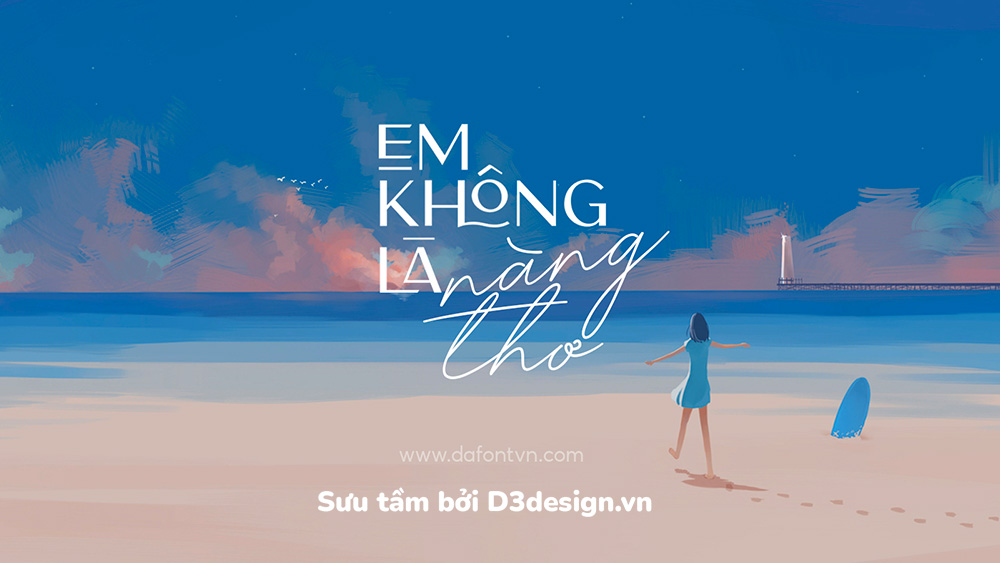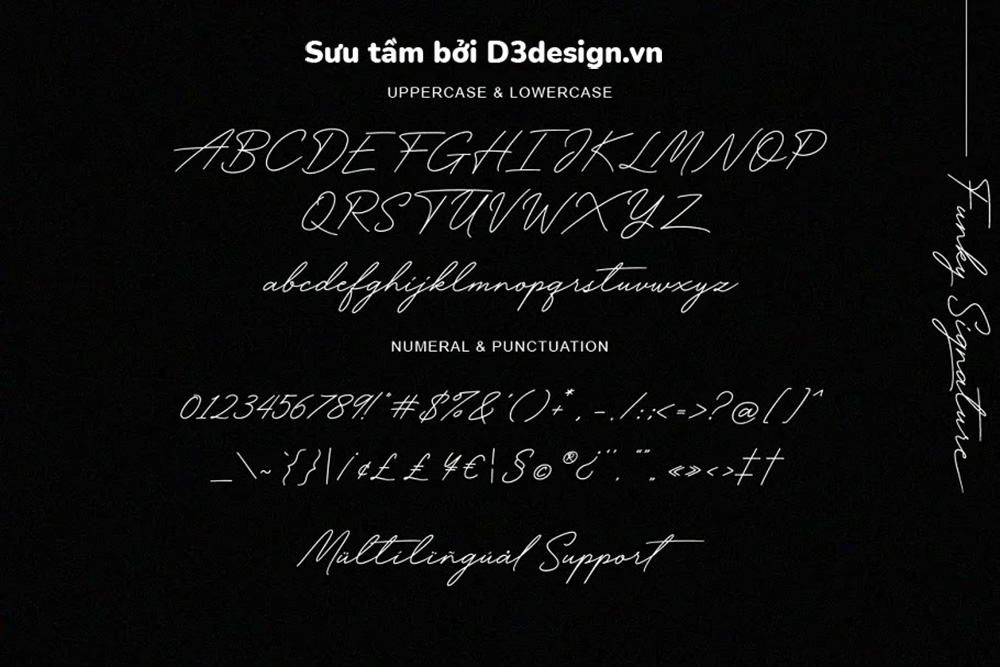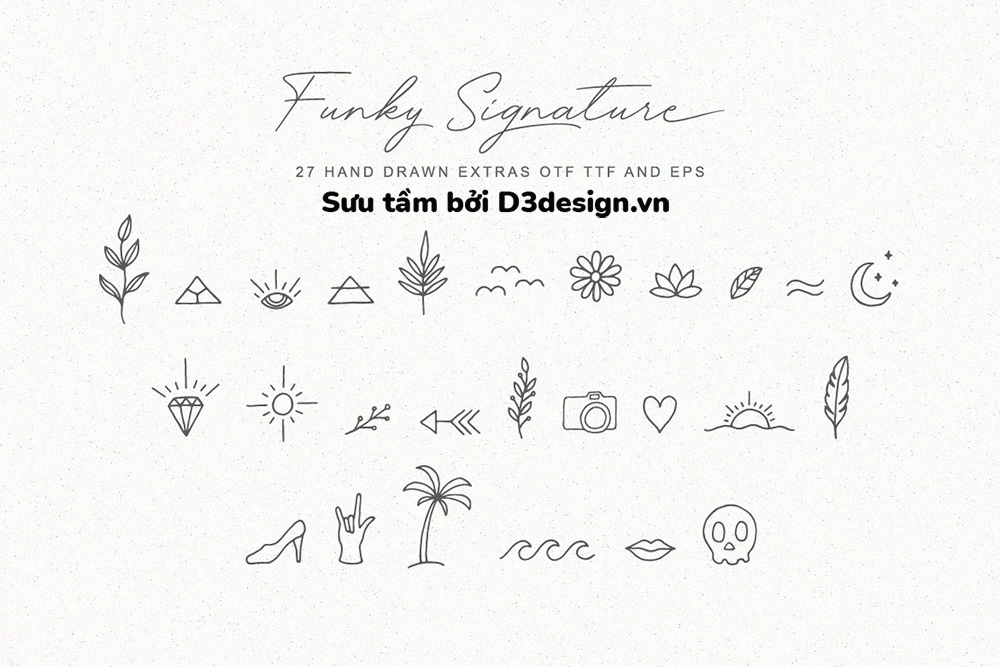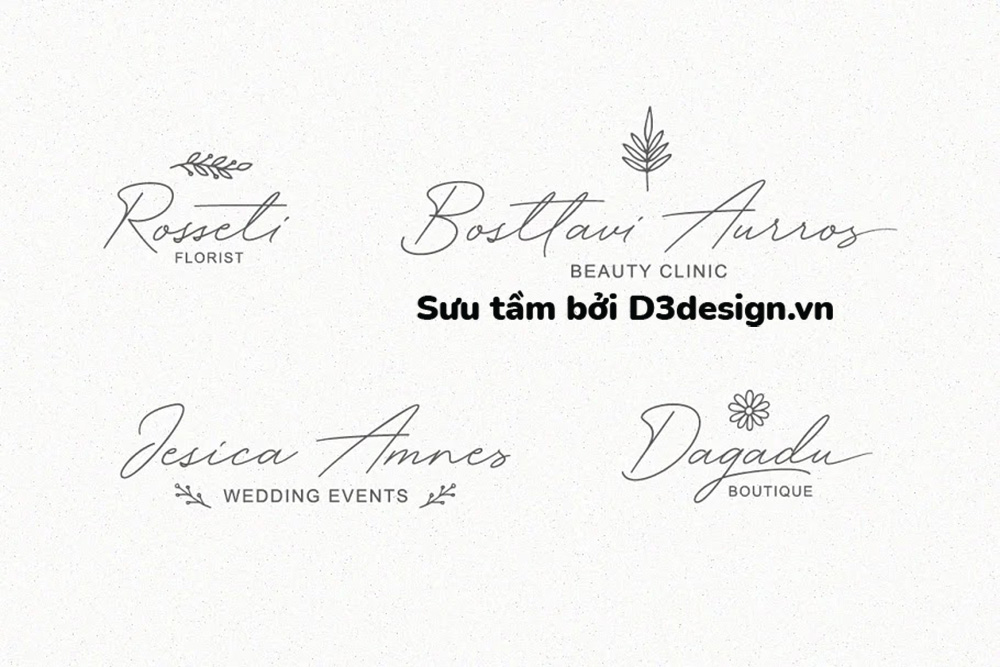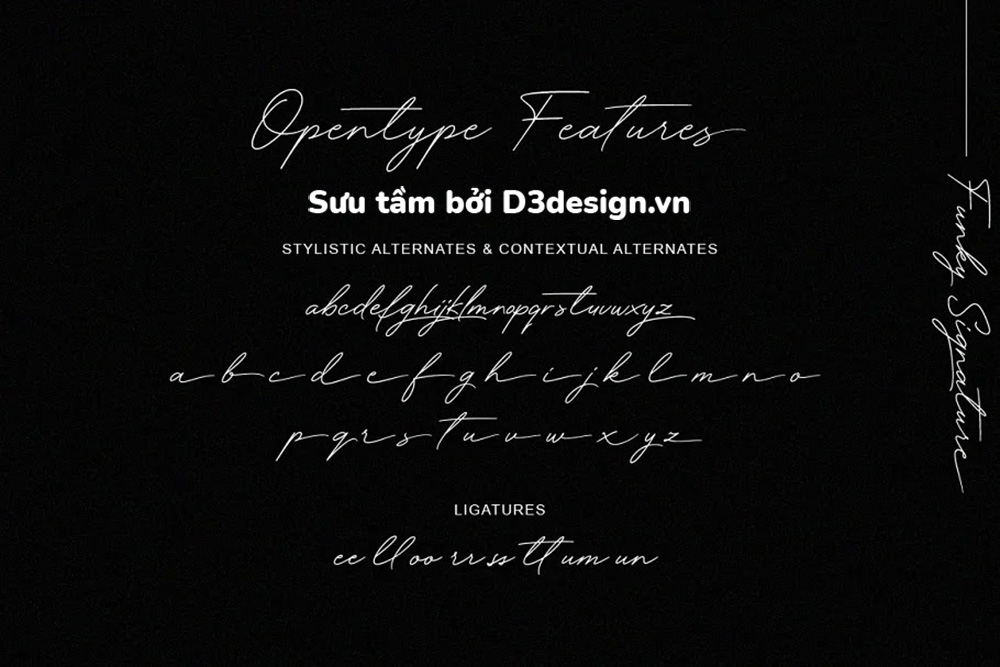
Font Việt Hóa - Signature Chữ Viết Tay Nét Đẹp Tự Nhiên Và Cổ Điển
Funky Signature Việt Hóa là một font chữ ký viết tay với các nét vẽ tự nhiên theo phong cách thập niên 80, hoàn hảo để xây dựng thương hiệu cá nhân, nhãn hiệu sản phẩm, bao bì, thư mời, danh thiếp, bìa phim và quảng cáo.
Funky Signature được trang bị nhiều tính năng bổ sung cho phép bạn tùy chỉnh văn bản của mình. Bạn sẽ nhận được một bộ hoàn chỉnh bao gồm chữ hoa và chữ thường, dấu chấm câu, chữ ghép, các kiểu thay thế, các tính năng bổ sung được vẽ tay mà bạn có thể kết hợp để tạo biểu trưng và các thay thế theo ngữ cảnh.